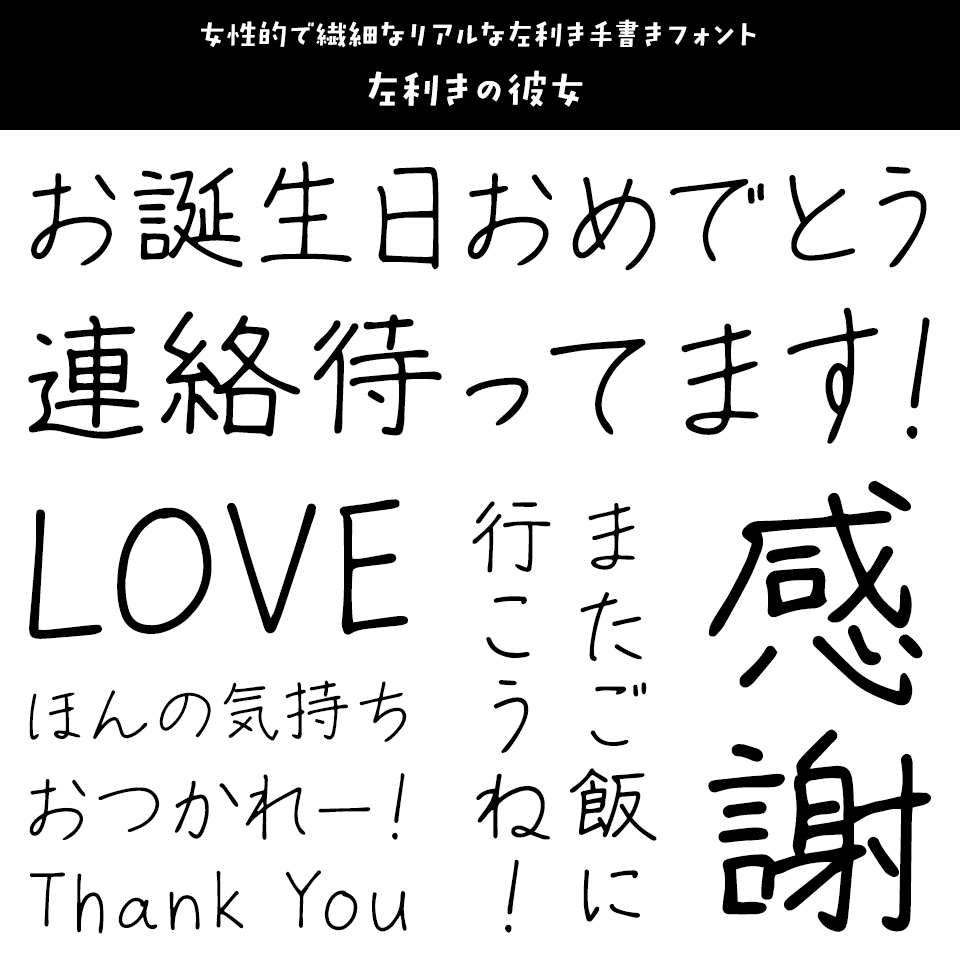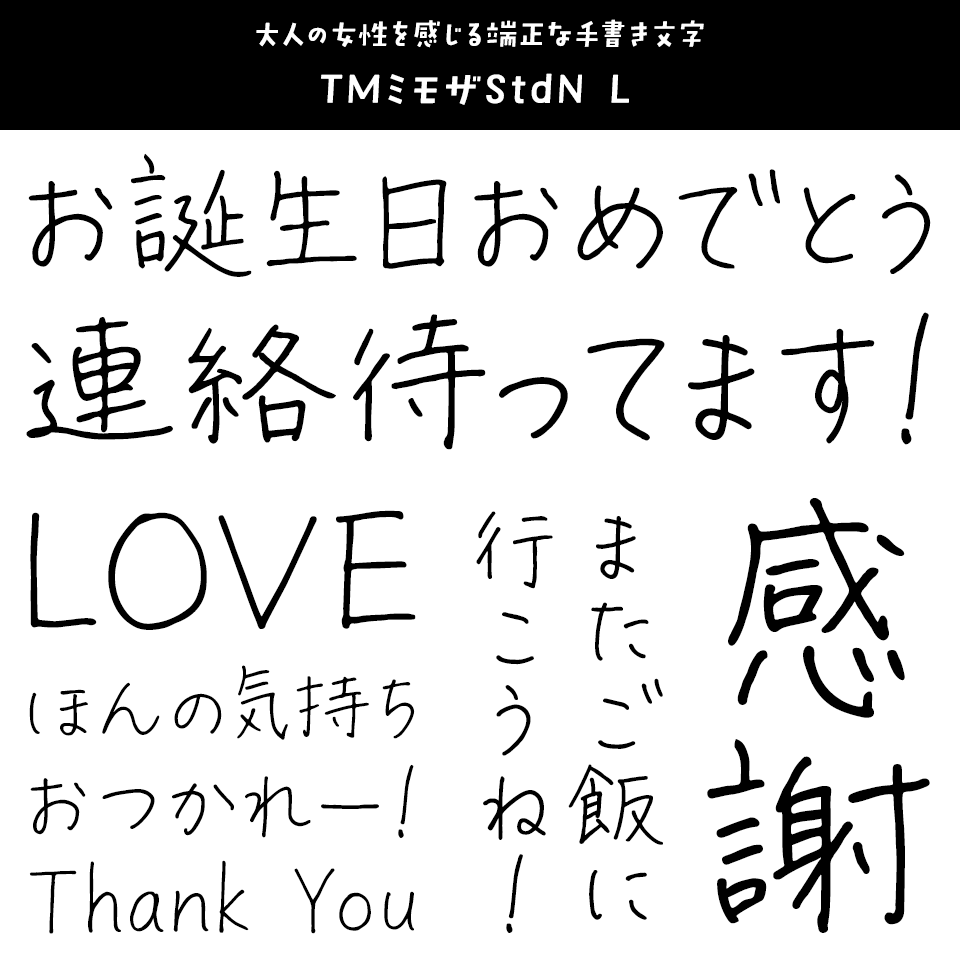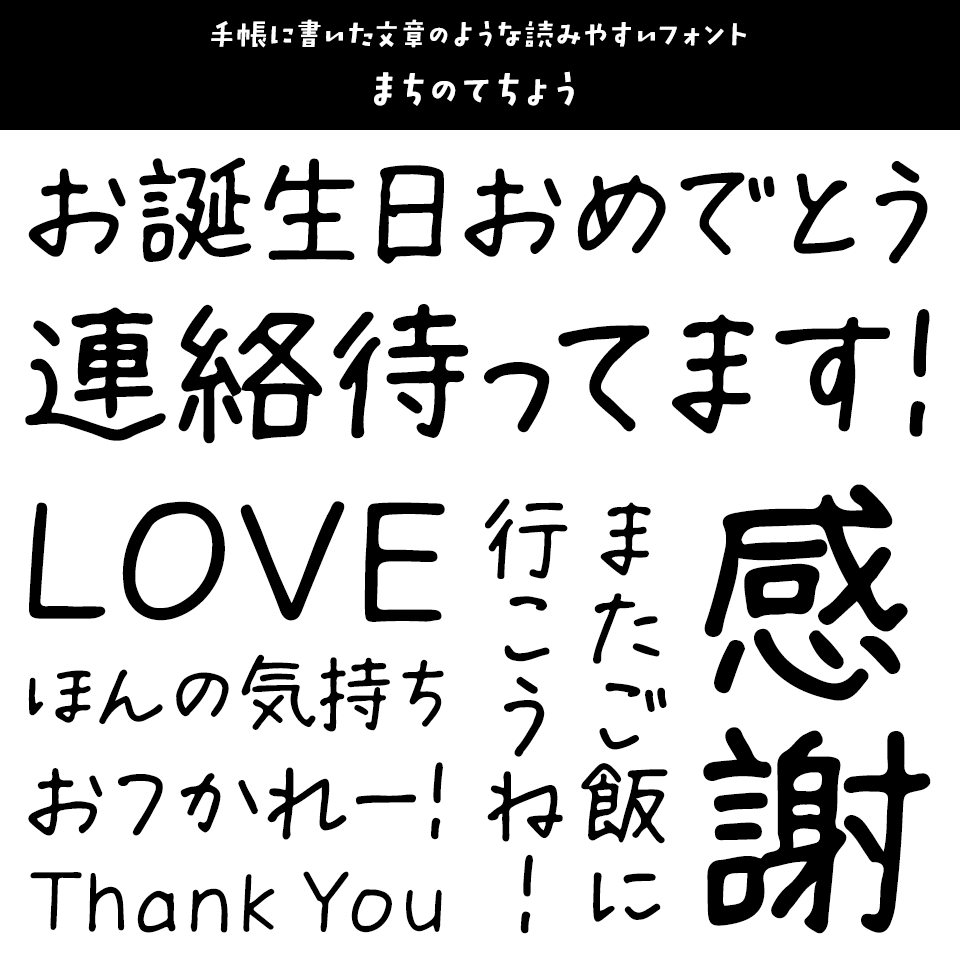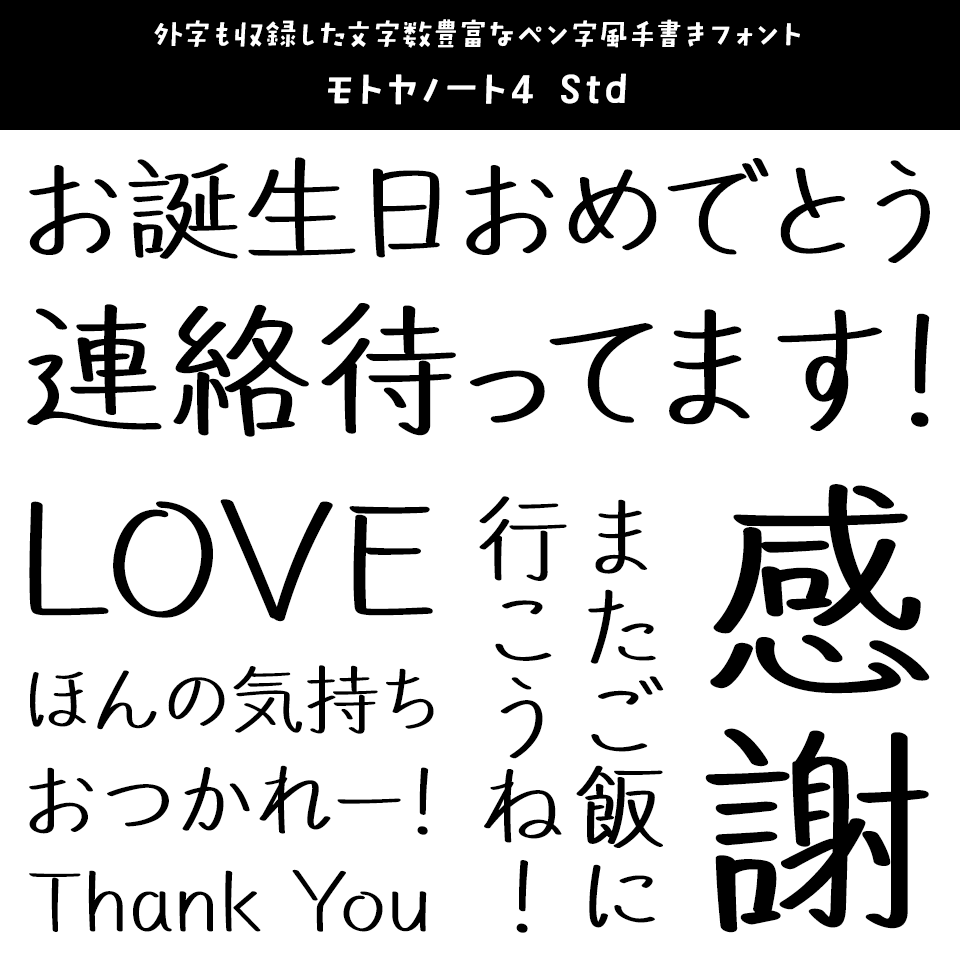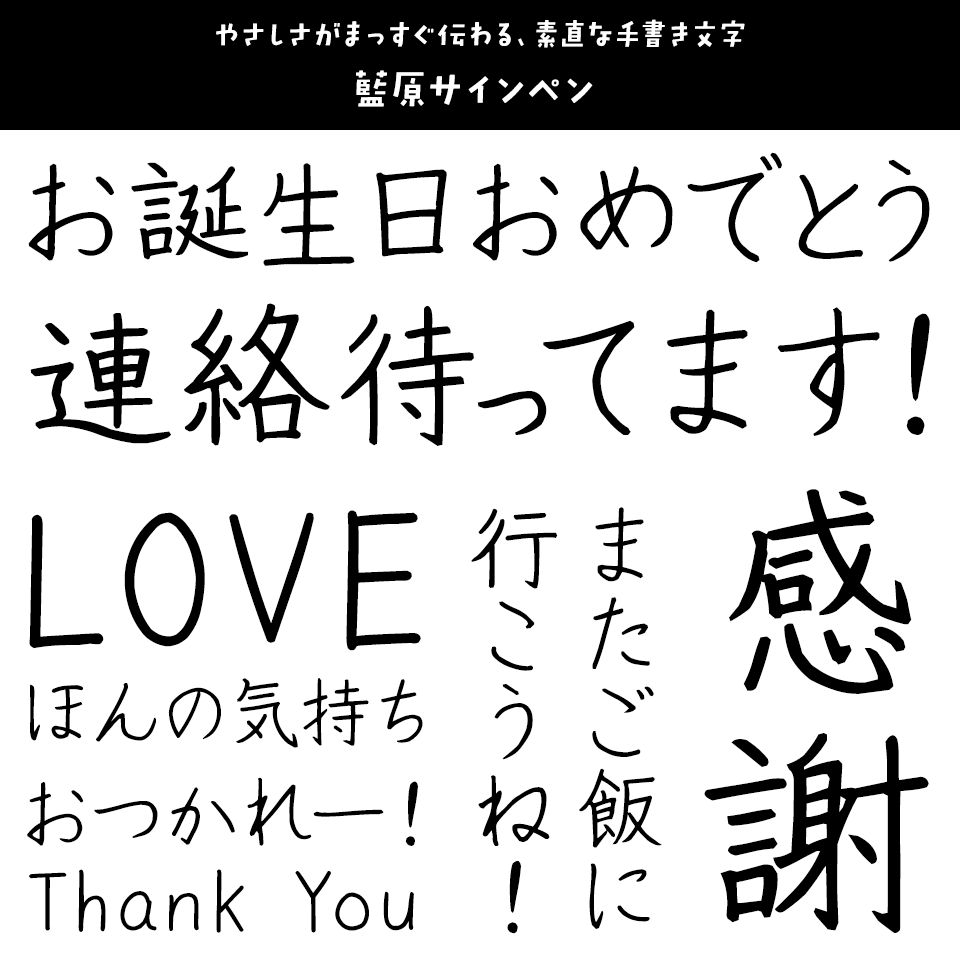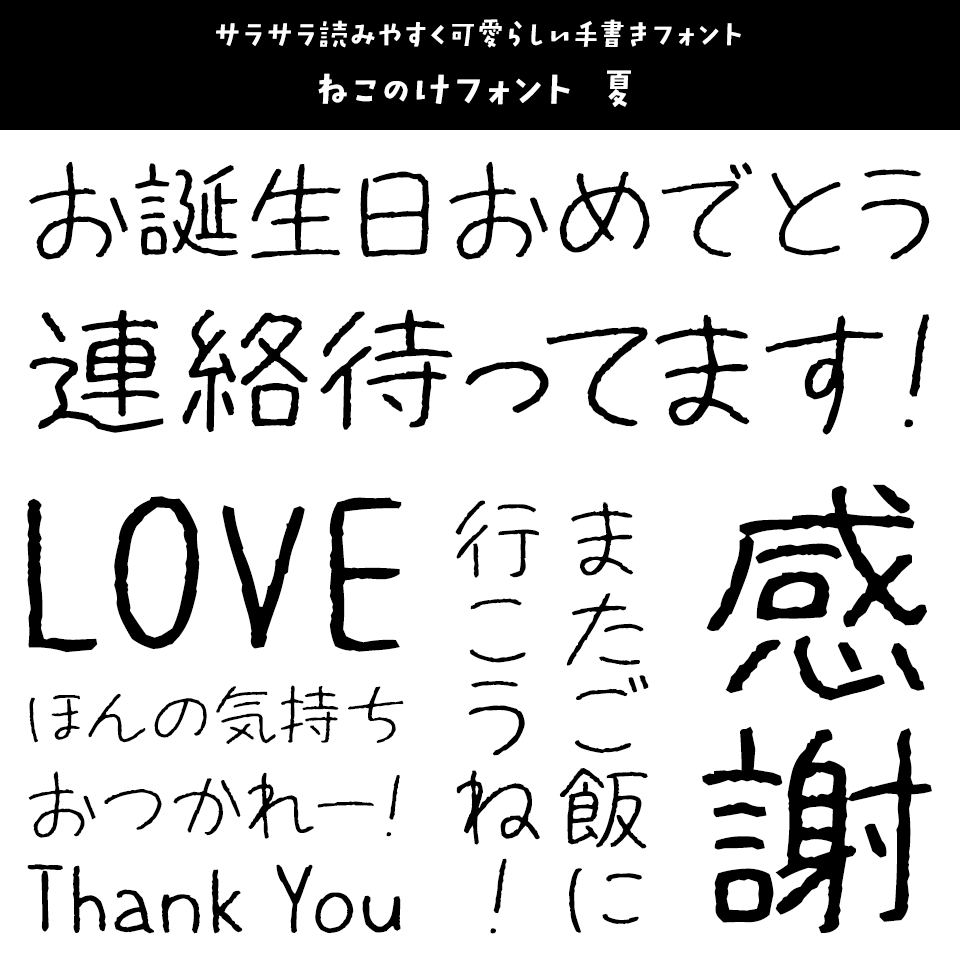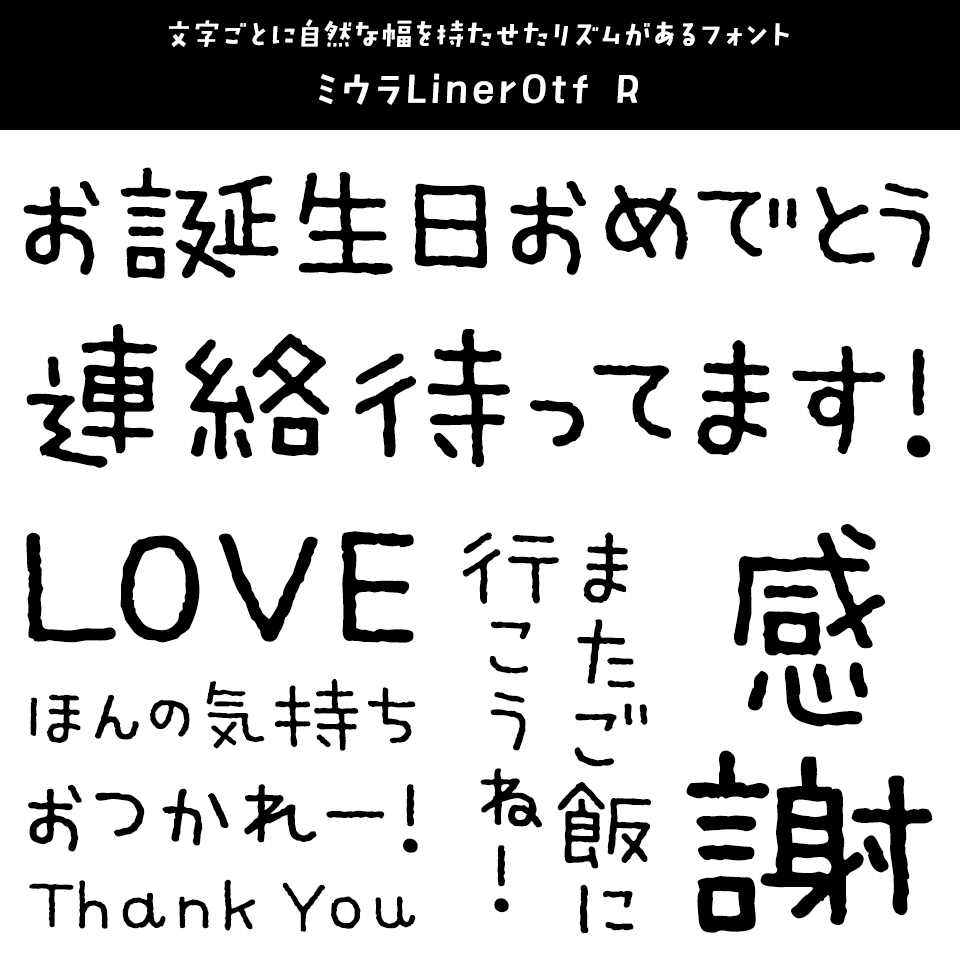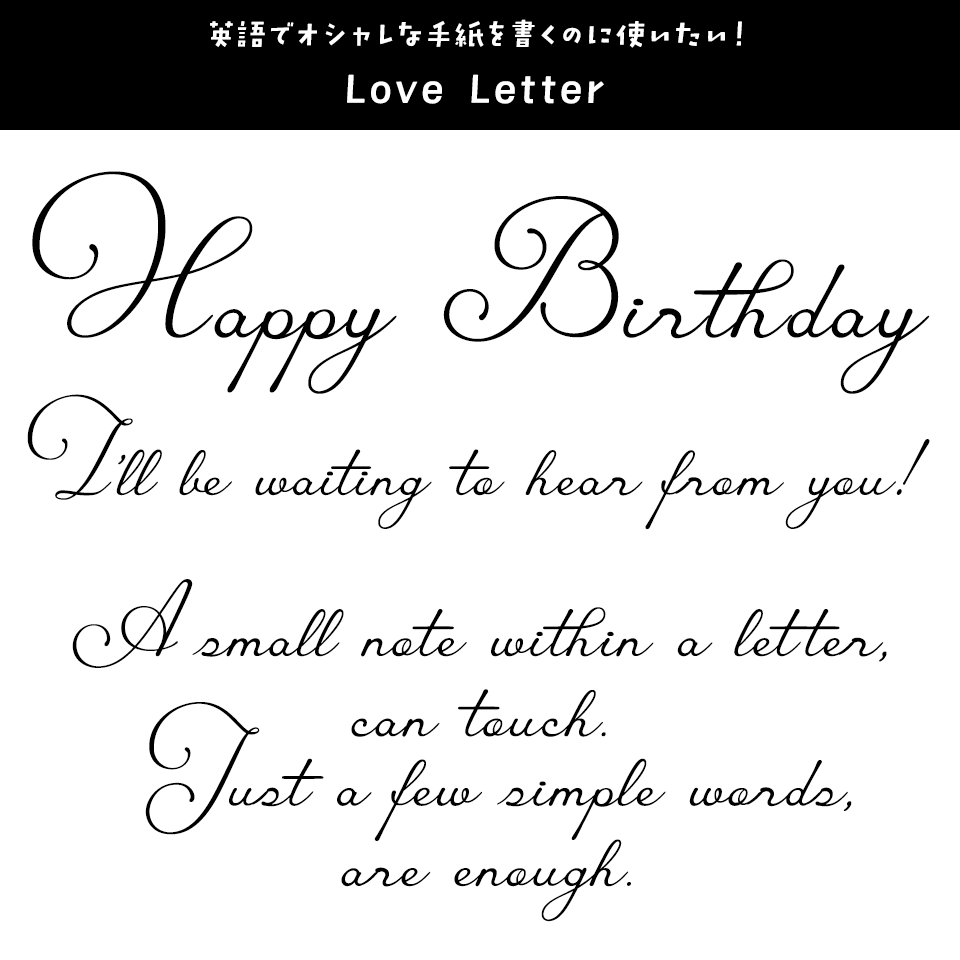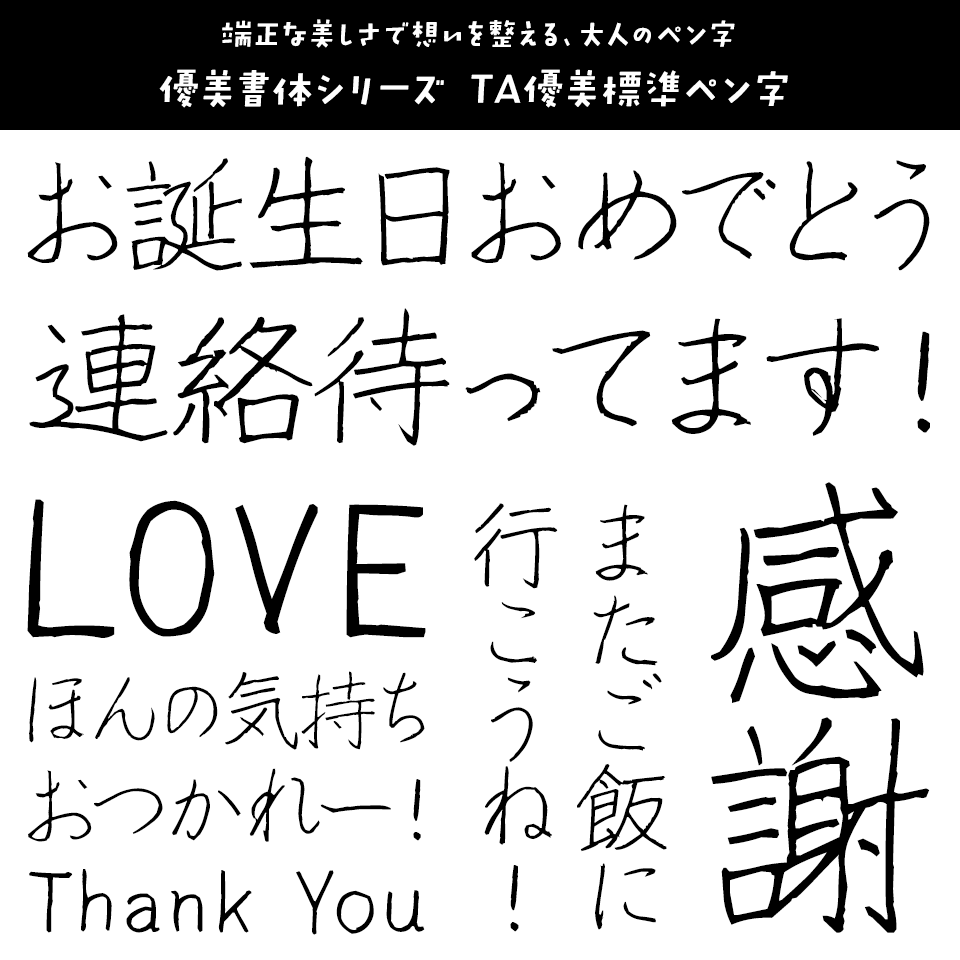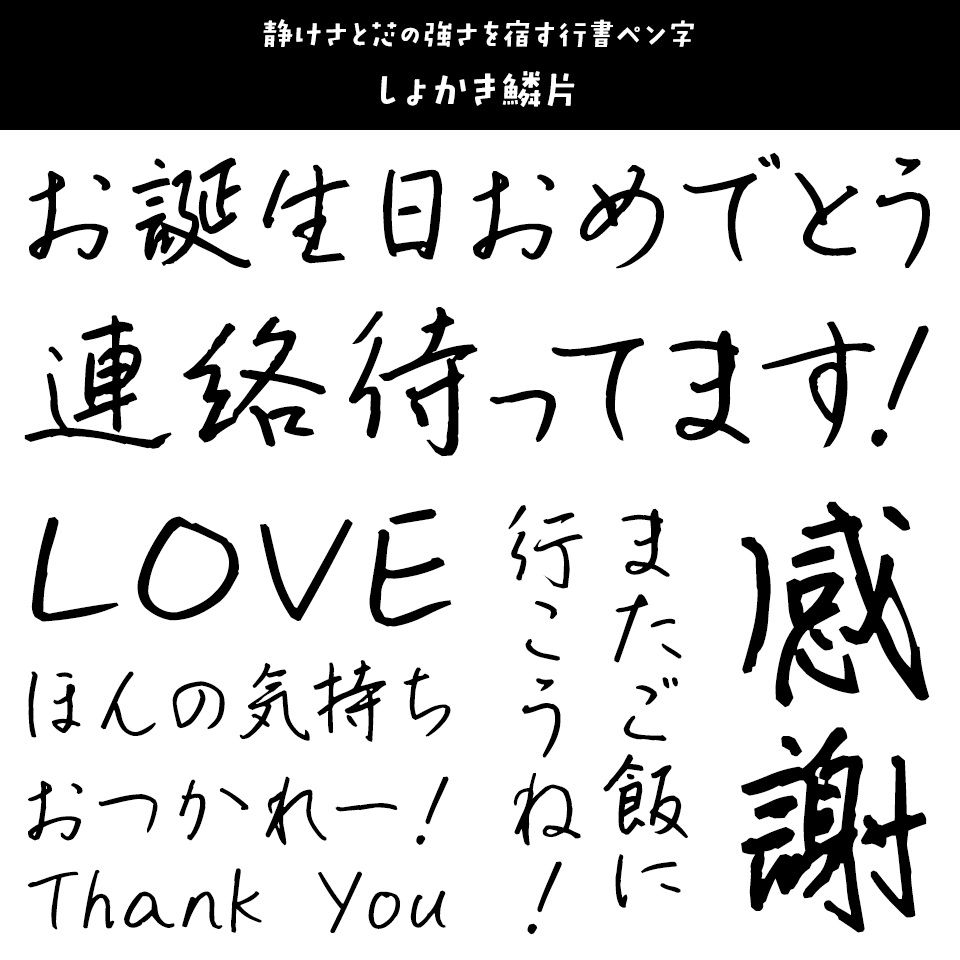
「便箋に添える文字」 左利きの彼女
女性的で繊細なリアルな左利き手書きフォント
▶左利きの彼女【Hitomi Shibuya】
「便箋に添える文字」 左利きの彼女
左利きの作者が丁寧に書いた手書き文字をフォントにしました。細くて少し小さい、繊細な印象のフォントです。
「便箋に添える文字」 TMミモザStdN L
大人の女性を感じる端正な手書き文字
▶TMミモザStdN L Std【タンデムフォント】
「便箋に添える文字」 TMミモザStdN L
ペンのにじみを残した、自然で穏やかな女性の手書き文字です。特典で収録の装飾素材もキレイ目で使える素材です。
「便箋に添える文字」 まちのてちょう
手帳に書いた文章のような読みやすいフォント
▶まちのてちょう【まち@machicooooo】
「便箋に添える文字」 まちのてちょう
スマホひとつで気軽に使える手書きフォント。iPadとApple Pencilで直筆から制作しました。手書きのやさしさを残しながら、長文でも読みやすく、手紙との相性もばっちりです。
「便箋に添える文字」 モトヤノート4 Std
外字も収録した文字数豊富なペン字風手書きフォント
▶モトヤノート4 Std【モトヤ】
「便箋に添える文字」 モトヤノート4 Std
ペンを走らせたときに生じる線の太さが不揃いになる点や、曲線的な表現が多くなる点など、フリーハンドならではの特徴を持つ書体です。
「便箋に添える文字」 藍原サインペン
やさしさがまっすぐ伝わる、素直な手書き文字
▶藍原サインペン【Faraway】
「便箋に添える文字」 藍原サインペン
丁寧で読みやすい線は、やわらかな女性らしさを感じさせつつ、素直で誠実な男性の手紙にも自然に馴染みます。家族への季節の便りや、友人への絵手紙、年賀状やポストカードにもぴったり。
「便箋に添える文字」 ねこのけフォント 夏
サラサラ読みやすく可愛らしい手書きフォント
▶ねこのけフォント 夏【ゆるてがきこむ】
「便箋に添える文字」 ねこのけフォント 夏
換毛期を終え、夏の暑さに備えた猫のスッキリした毛並みをイメージしたさらっと細字の手書き日本語フォントです。ねこのけフォント夏、ねこのけフォント夏Boldの2ウェイトを収録。
「便箋に添える文字」 DSありんこ
文字の始まりとトメの部分に丸みを残した可愛いフォント
▶DSありんこ【七種泰史/デザインシグナル】
「便箋に添える文字」 DSありんこ
ころころと丸みのあるフォルムが愛らしく、小さな“ありんこ”が並ぶような、リズム感のある文字デザインが特長です。
「便箋に添える文字」 ミウラLinerOtf R
文字ごとに自然な幅を持たせたリズムがあるフォント
▶ミウラLinerOtf R【ミウラフォント/モップスタジオ】
「便箋に添える文字」 ミウラLinerOtf R
手書き文字らしさを生かすために全ての文字を可変幅(プロポーショナル)で作成した特殊なフォント。「ぐちゃっ」とした書き直し筆跡など、オリジナルの記号も魅力です。
「便箋に添える文字」 Love Letter
文英語でオシャレな手紙を書くのに使いたい!
▶Love Letter【satsuyako】
「便箋に添える文字」 Love Letter
ロゴにも長文にも使えるスクリプト体フォントです。デフォルトはスタンダードな筆記体となっています。
「便箋に添える文字」 優美書体シリーズ TA優美標準ペン字
端正な美しさで想いを整える、大人のペン字
▶優美書体シリーズ TA優美標準ペン字【スキルインフォメーションズ】
「便箋に添える文字」 <strong>ミウラLinerOtf R</strong>
優雅さと整然とした美しさを追求した上品なペン字書体。くずしすぎない端正な線は、落ち着いた女性の丁寧な手紙にも、誠実な男性の挨拶状にも自然に調和します。
「便箋に添える文字」 しょかき鱗片
静けさと芯の強さを宿す行書ペン字
▶しょかき鱗片【しょかき/ぼんのう堂】
「便箋に添える文字」 しょかき鱗片
手書き由来の揺らぎと鱗のような線の表情が、便箋に書く言葉へ静かな気品を添えます。凛とした女性が綴る季節の便りにも、寡黙で誠実な男性がしたためる挨拶状にも似合うフォントです。